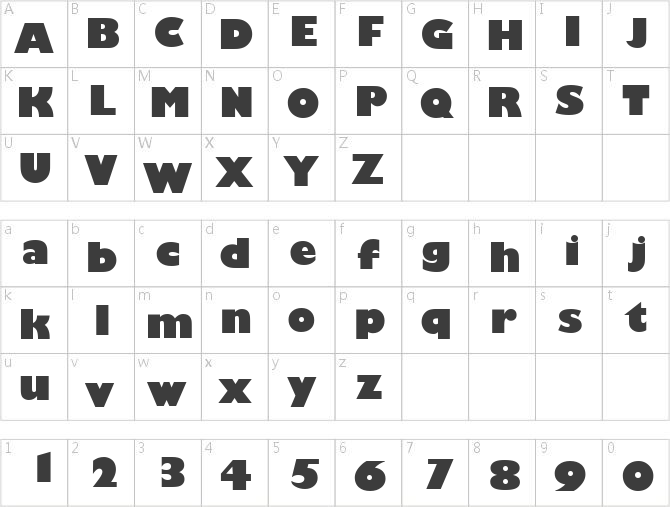
字體名稱: Gentle
Gentle Sans Ultra Bold
Gentle Sans Ultra Bold介紹
Gentle Sans Ultra Bold字體字庫是一款讓人賞心悅目、百看不厭的英文字體,適合各類廣告和產品包裝設計應用,字體大小0.04MB,格式為ttf字體,上傳用戶是澤澤,作者/版權方為未知